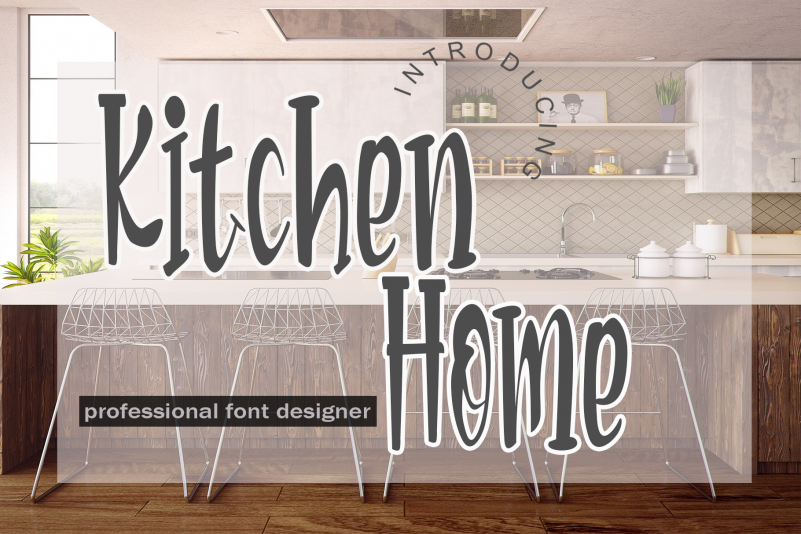
Kitchen Home Font – Fonte Grátis
Kitchen Home Font
Esta é uma fonte de exibição de estilo cool e quirk, ideal para quem valoriza a criatividade e gosta de incorporar elementos únicos nos trabalhos. Perfeita tanto para títulos como para letras personalizadas, esta fonte vai se destacar em cartazes, logotipos e materiais gráficos pessoais ou industriais. Ela combina bem com um leque variado de ideias, desde cartões de visita até revistas pessoais, fazendo dela uma excelente opção para quem busca personalizar seu design de maneira única e moderna. Inspirada no designer KateEngciu, esta fonte pertence à categoria Display Fonts, onde cada traço convida a explorar diferentes estilos e usos, garantindo um resultado visual inovador para qualquer projeto.